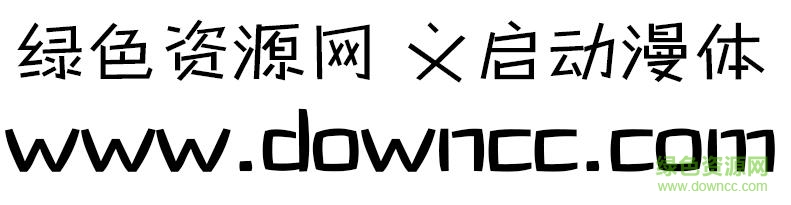
義啟動(dòng)漫體是一款義啟類動(dòng)漫風(fēng)格字體軟件,動(dòng)漫體以灑脫清新的外形給人非常自由的感覺,適合動(dòng)漫行業(yè)標(biāo)題內(nèi)容書寫,也深受廣大書法家的喜愛,還有更多好看字體盡情期待,歡迎到綠色資源網(wǎng)下載體驗(yàn)!
義啟動(dòng)漫體賦予動(dòng)畫和漫畫新的含義,即“動(dòng)感十足”和“漫不經(jīng)心”。 義啟動(dòng)漫體,章法律動(dòng)上更接近手寫,左右忽悠感很強(qiáng),字間距把握考究,整體氣息舒暢爽朗。結(jié)構(gòu)上顯得動(dòng)感十足